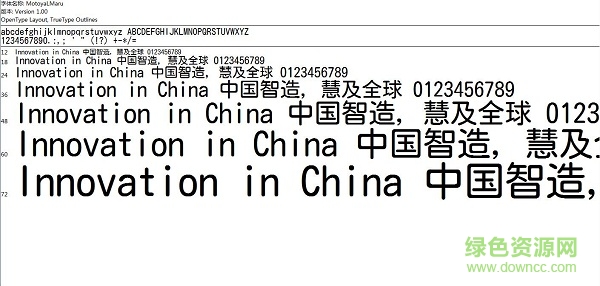
mtlmr3m.ttf是什么?mtlmr3m.ttf是日文字體motoyalmaru w3字體的縮寫,圓潤流暢,字距緊湊,易讀易辨識(shí),具有豐富的實(shí)用性,有需要者歡迎免費(fèi)下載!
基本上分為兩類,中文里面「宋體」「黑體」這兩類,日語習(xí)慣上稱為「明朝體」(Mincho)「哥特體」(Gothic)。一般來說印刷品的書籍和報(bào)紙正文采用明朝體,有部分雜志正文采用哥特體,而網(wǎng)絡(luò)基本上都是哥特體。